モリサワが邦文写真植字機発明100周年を皮切りに写研書体のOpenTypeフォント開発で今後100フォントをリリースすることを発表
モリサワと写研による写研書体のOpenTypeフォント開発プロジェクトの続報として、今後数年以内に合計100フォントに及ぶ写研書体のOpenTypeフォントのリリースが予定されていることが、モリサワから2024年2月13日に発表となった。
2024年の提供書体には「石井明朝・石井明朝オールドスタイルかな」「石井ゴシック」の13フォントと、写研のバリエーション豊かな見出し書体群を「写研クラシックス」としてOpenType化した30フォント、合計43フォントを予定。
2025年以降もこれらに続くラインナップを順次提供予定となるそうだ。
写研書体にとって新しい歴史の幕が開く2024年は、邦文写真植字機の発明100周年を迎える節目の年となる。
今後も、過去から未来へとつながる多彩な写研書体を提供されていくとのこと。
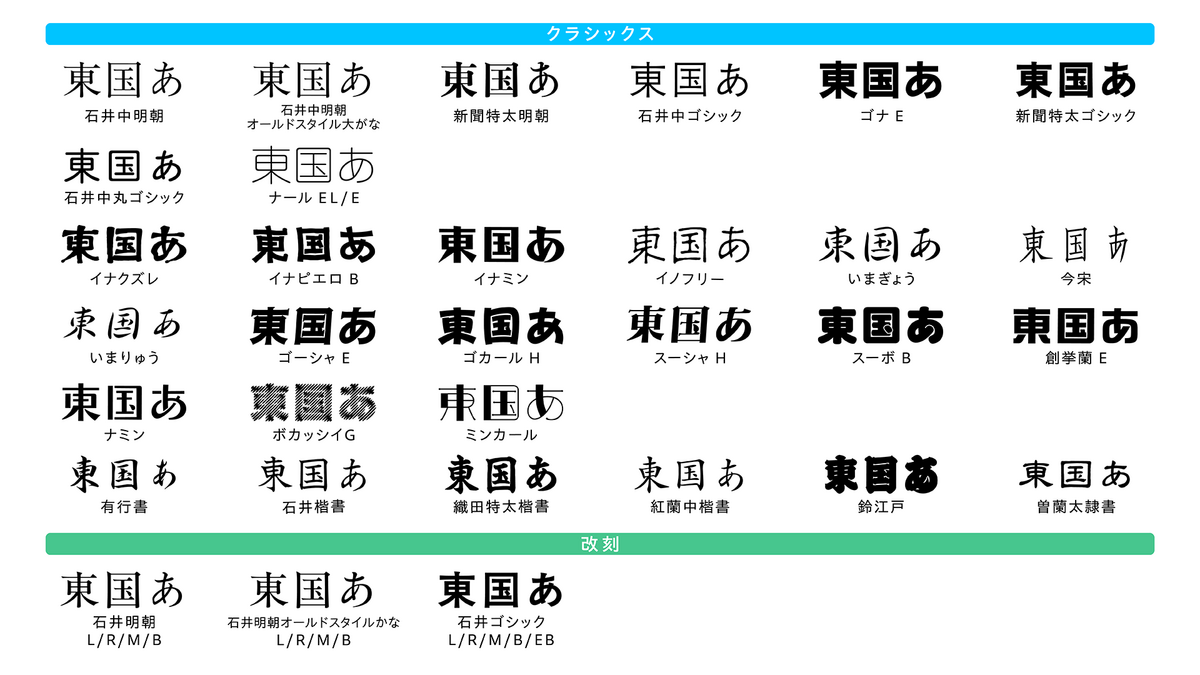
写研クラシックス
「写研クラシックス」は、多種多様な名作見出し書体群が、写植全盛期の味わい深いデザインそのままに使用できるフォント。
モリサワは写研から提供を受けたアウトラインデータに加えて不足文字の作成や文字セットなどの仕様の整理を行った。
見出し利用に特化させ、従来写真植字機でのみ利用可能だった多くの写研書体と、写真植字機時代に発表されていない書体を、現代のOpenTypeフォントとして再現した。
なお、改刻フォントは「写研クラシックス」とは異なる開発アプローチや仕様を採用しているとのこと。
写研のコメント
昭和から平成にかけて、書籍・マンガ・広告などのあらゆる誌面や画面を彩ったかつての写研の書体群を、書体の形状イメージはそのままに高品位デジタル化し、一部かなについては写植時代でも表現されなかった詳細なストロークで、書体原図より忠実に復刻し再現しました。この度、モリサワ社との協業により、OpenTypeフォントとしてリリースされることを大変うれしく思います。生まれ変わった写研書体をぜひご利用ください。
2024年に提供開始を予定している写研フォント 概要
▼改刻フォント
石井明朝 L / R / M / B
石井明朝オールドスタイルかな L / R / M / B
石井ゴシック L / R / M / B / EB
▼写研クラシックス
有行書
石井楷書
石井中ゴシック
石井中丸ゴシック
石井中明朝
石井中明朝オールドスタイル大がな
イナクズレ
イナピエロ B
イナミン
イノフリー
いまぎょう
今宋
いまりゅう
織田特太楷書
ゴーシャ E
紅蘭中楷書
ゴカール H
ゴナ E
新聞特太ゴシック
新聞特太明朝
創挙蘭 E
曽蘭太隷書
スーシャ H
スーボ B
鈴江戸
ナール EL / E
ナミン
ボカッシイG
ミンカール